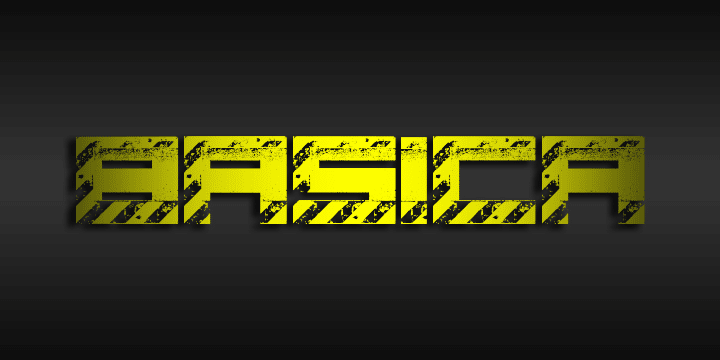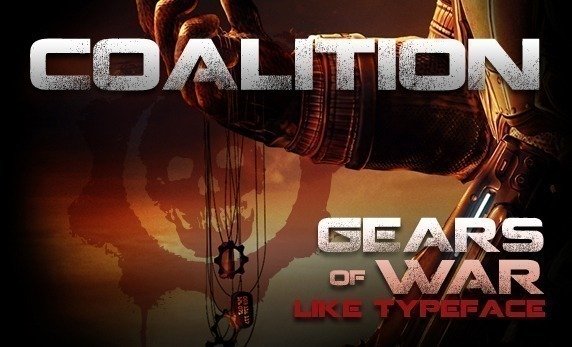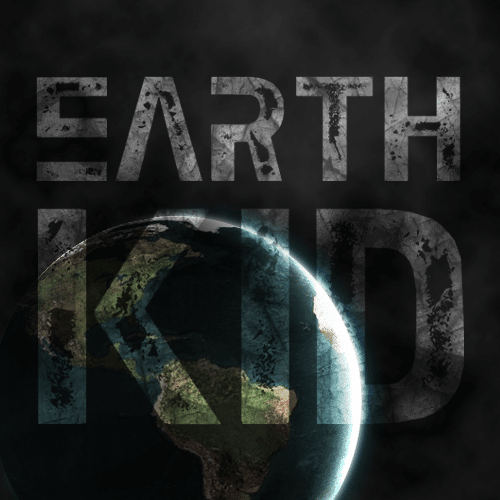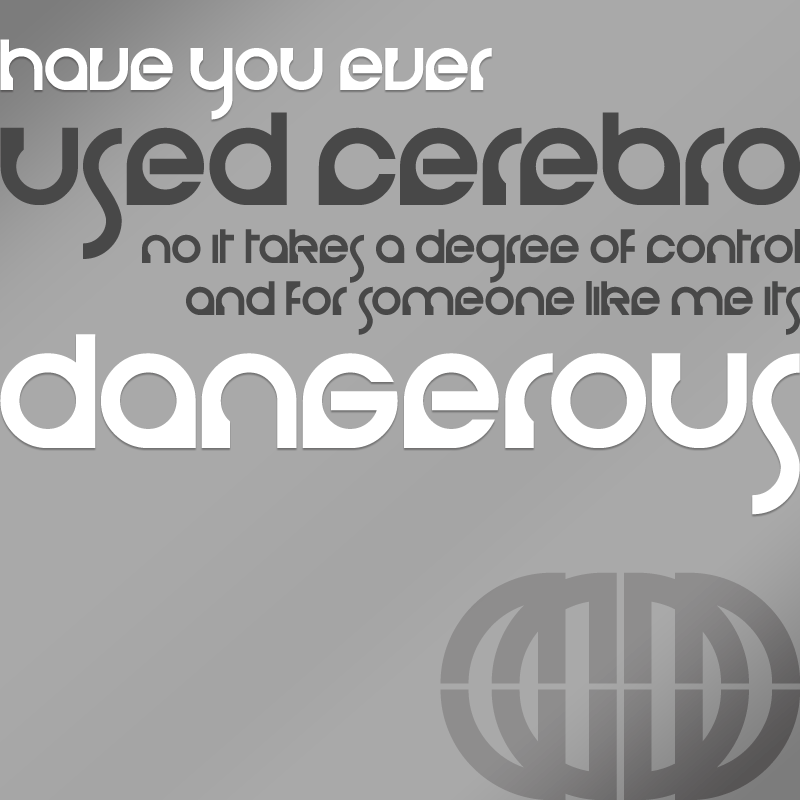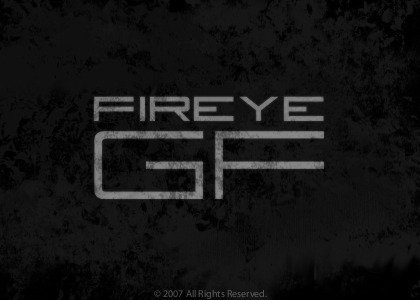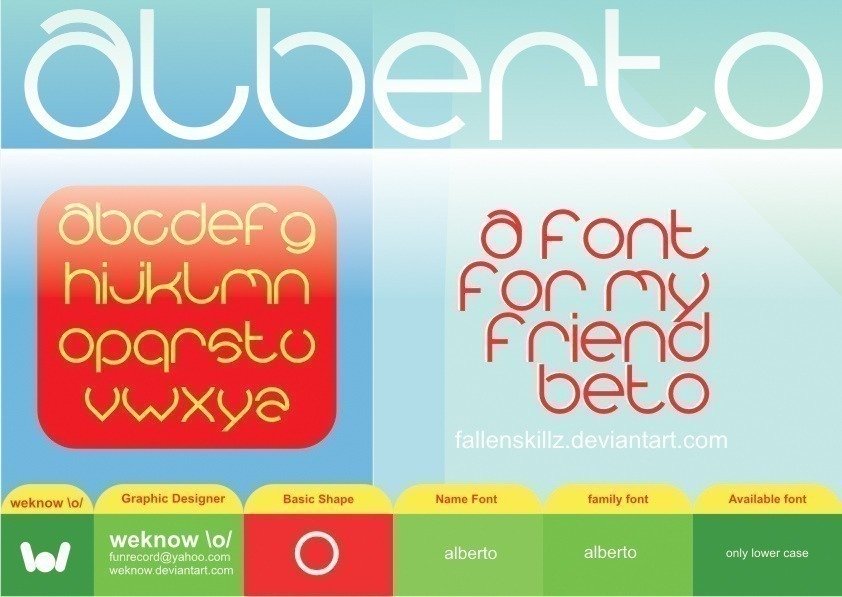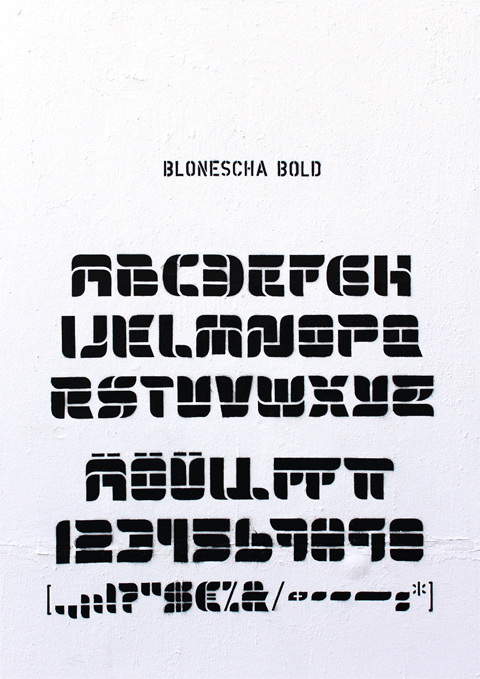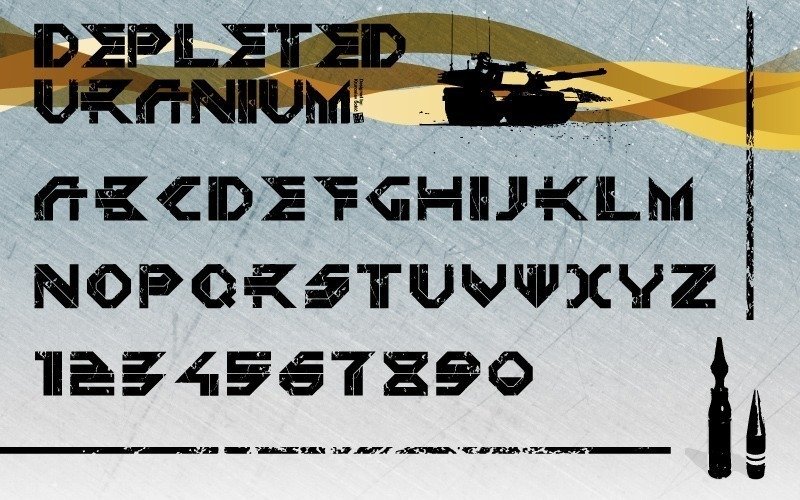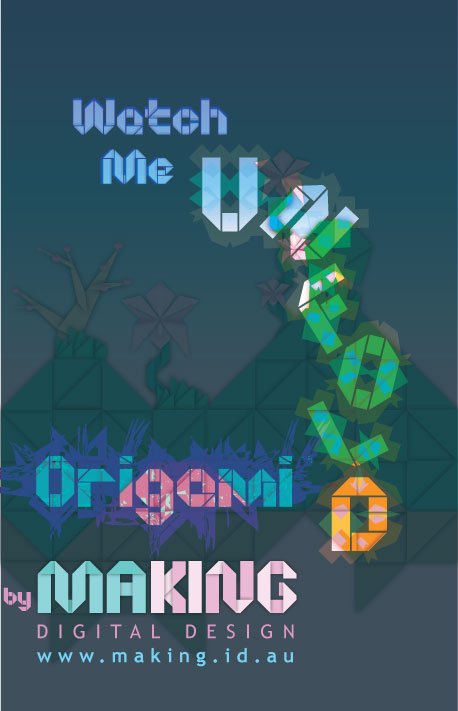
10 fontes Sci-fi gratuitas para download
Já precisou de fontes que remetessem à tecnologia, inovação, ficção científica?
Se ainda não, seria bom começar a criar uma coleção delas, pois nunca se sabe quando irá precisar.
1) Basica Industrial
2) Coalition
3) Earth Kid
4) Cerebro
5) Fireye GF
6) Alberto
7) Normal
8) Blonescha
9) Depleted Uranium
10) Origami Making